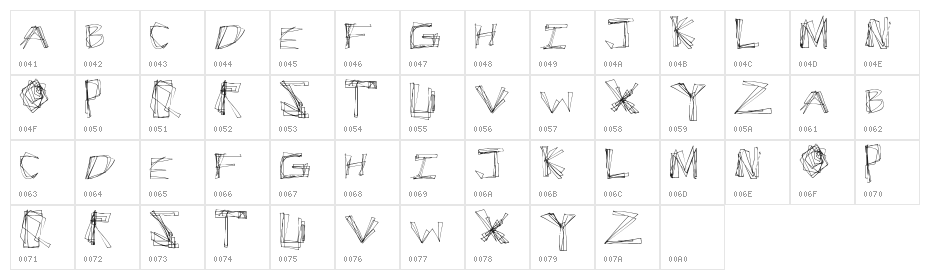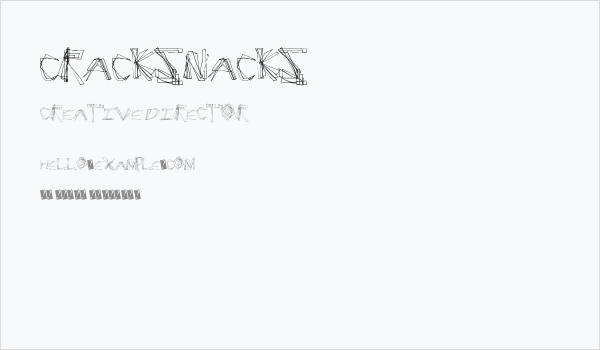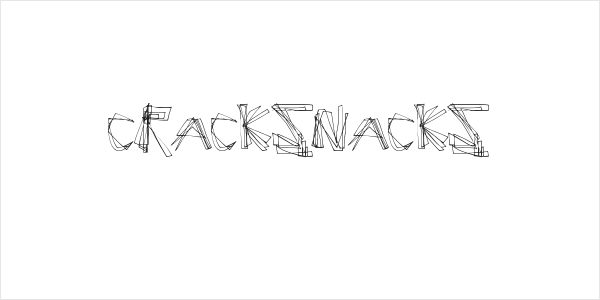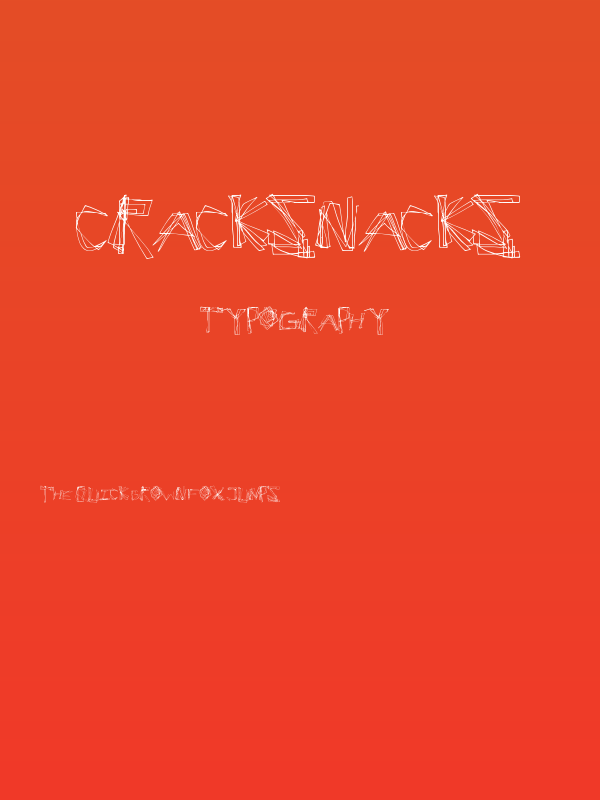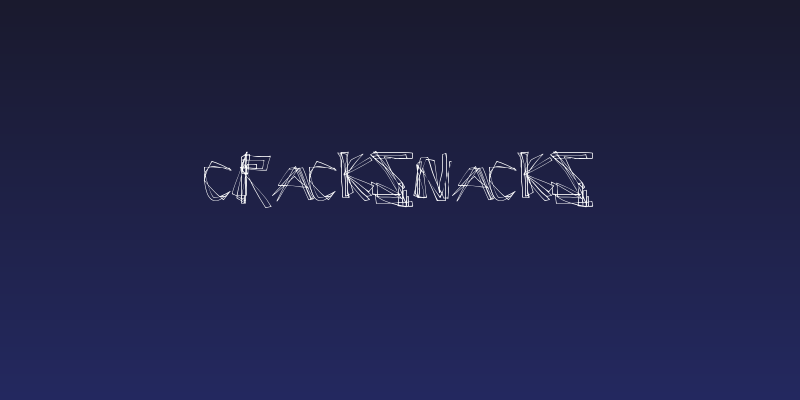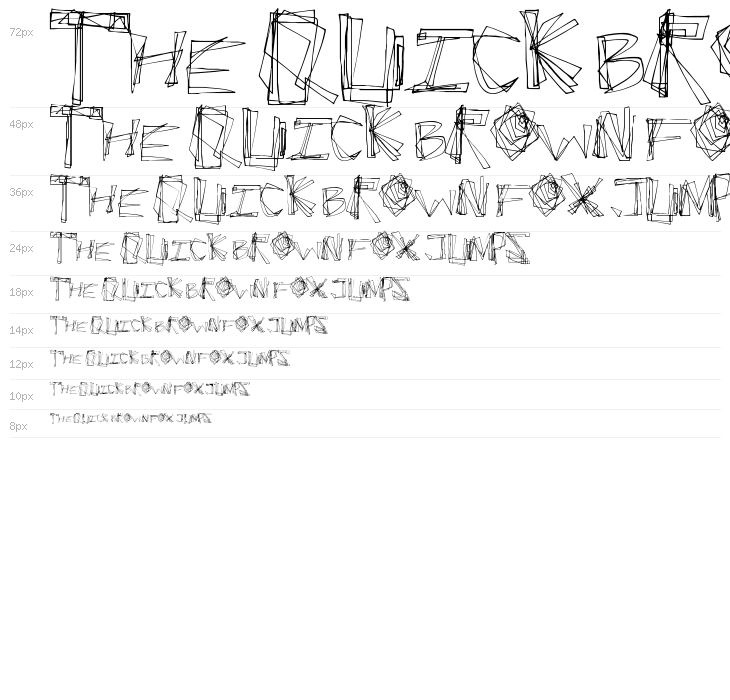
CrackSnacks Font
| Stile generale | Avant-garde, Artistic |
| Caso d'uso | Logos, Posters, Creative Branding |
| Progetti proposti | Ideal for artistic projects, album covers, posters, and creative branding that seeks to make a bold statement. |